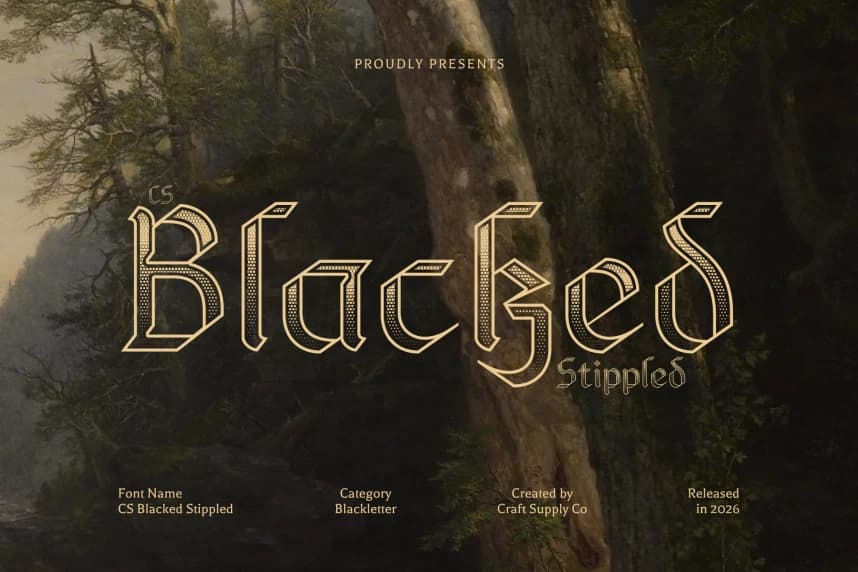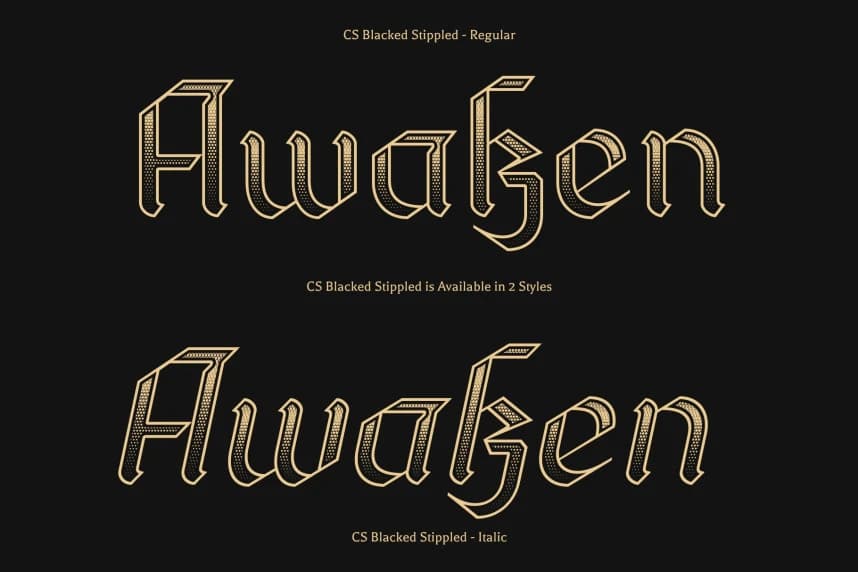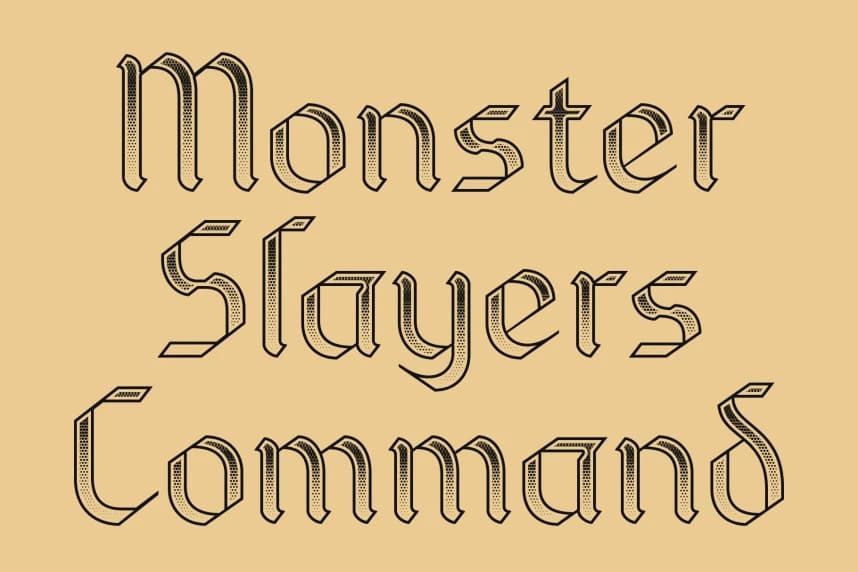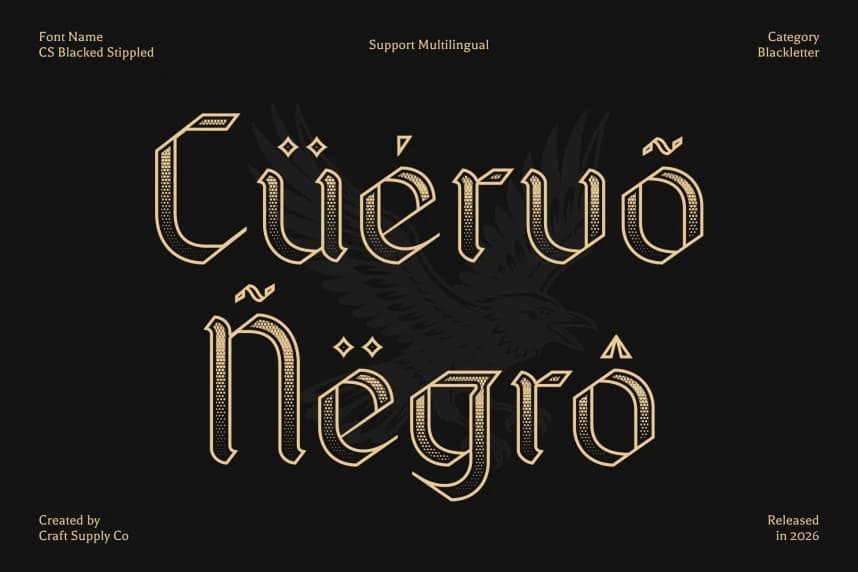
CS Blacked Stippled Yazı Tipi
CS Blacked Stippled Font – Blackletter Font: Blackletter Heritage ile Dokulu Tarihî Cazibe ve Display Serif ile Klasik Zarafet. Bu, geleneksel Blackletter tasarımının zamansız zarafetini kucaklayan çarpıcı bir display serif yazı tipidir.
CS Blacked Stippled Yazı Tipi – Blackletter Font: Klasik Zarafet, Dokulu Tarihsel Cazibe ile Görüntü Serif, Blackletter Mirası ile. Bu, geleneksel Blackletter tasarımının zamansız zarafetini kucaklayan çarpıcı bir görüntü serif yazı tipidir.